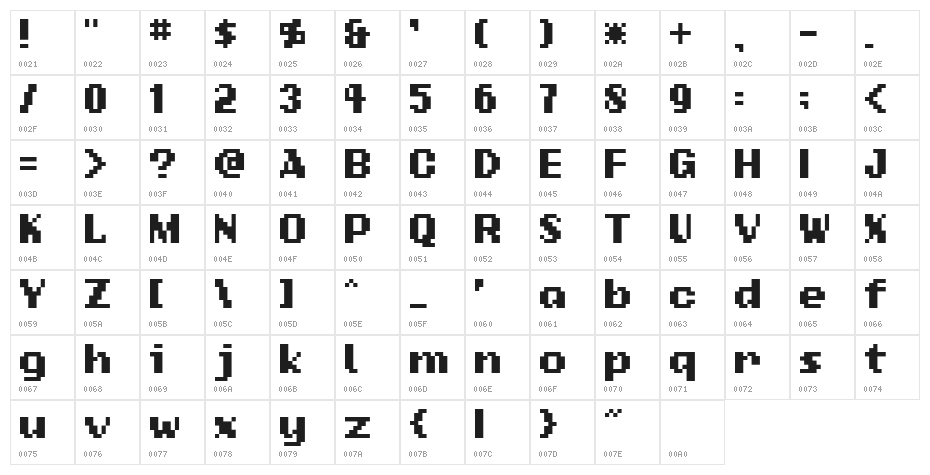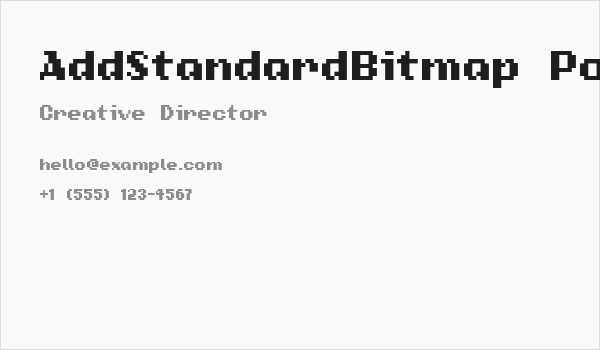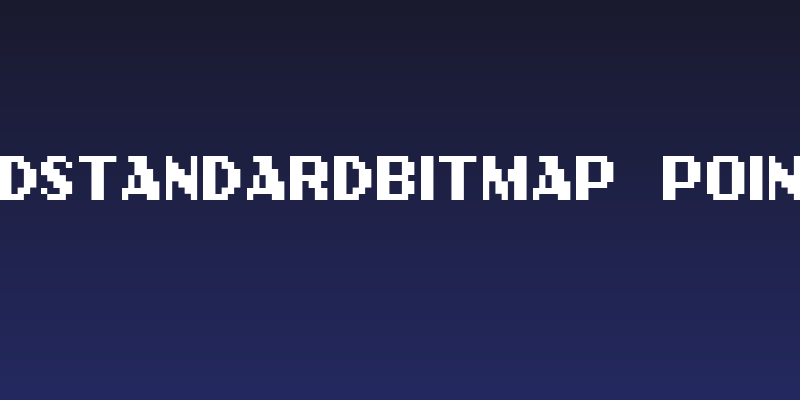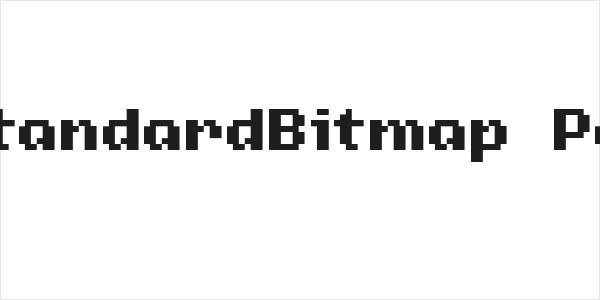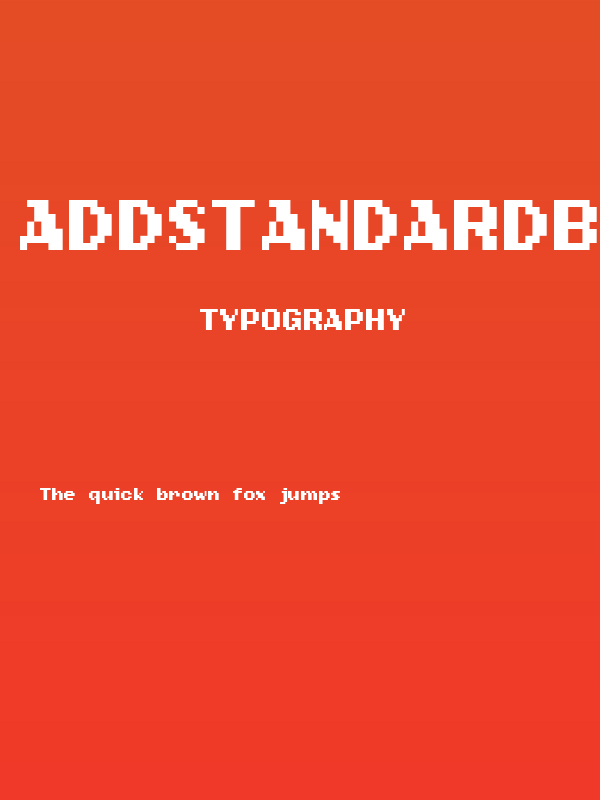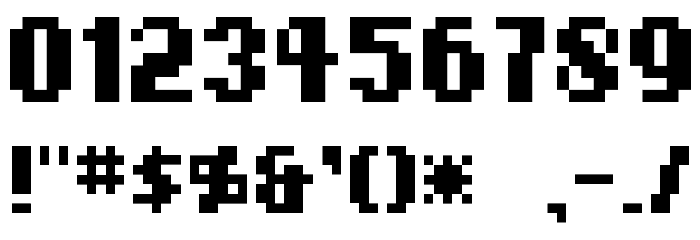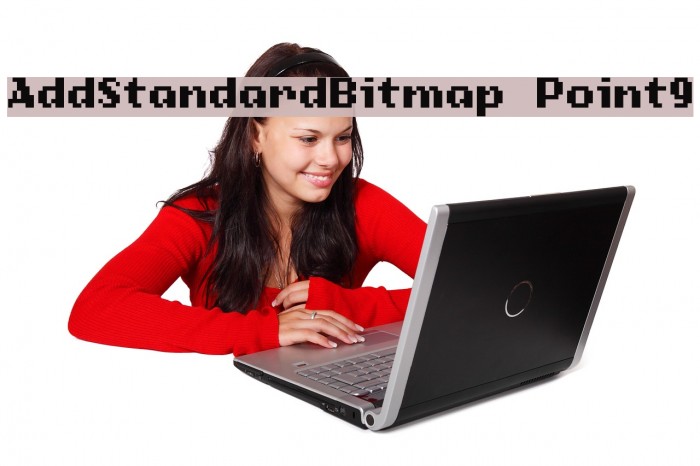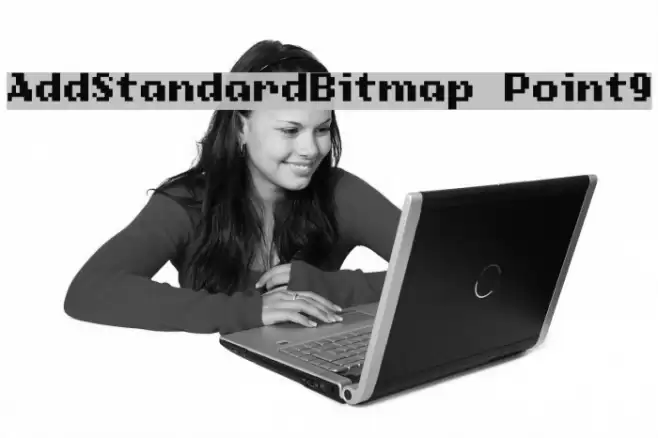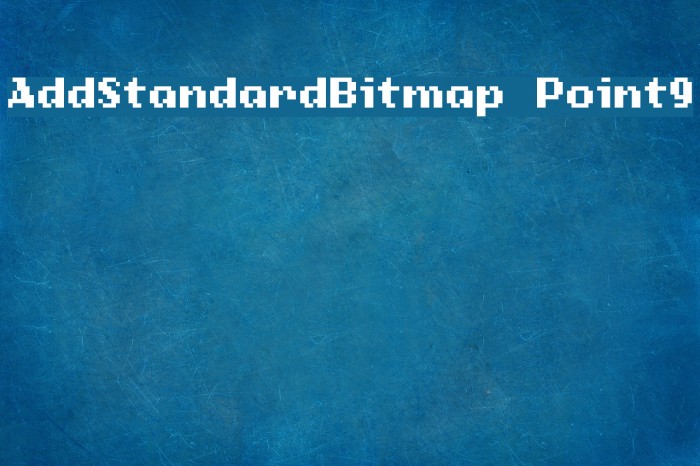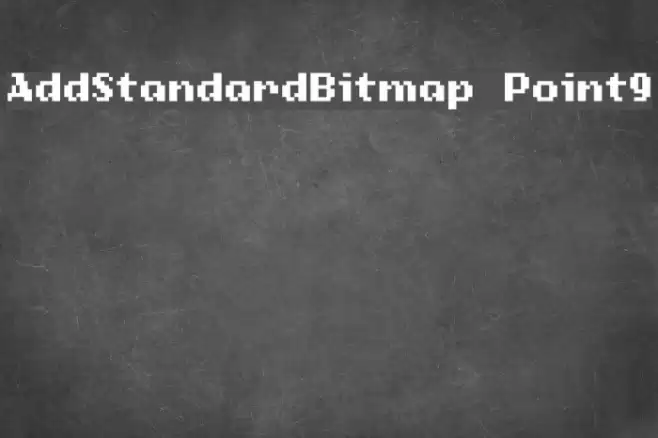
AddStandardBitmap Point9 Font
✎ Pixel
| カテゴリ | Pixel |
| 用途 | Logos, Headlines, Digital Art |
| おすすめプロジェクト | Ideal for retro-themed designs, video game graphics, digital art projects, and any creative work that seeks to evoke nostalgia for early computing. |